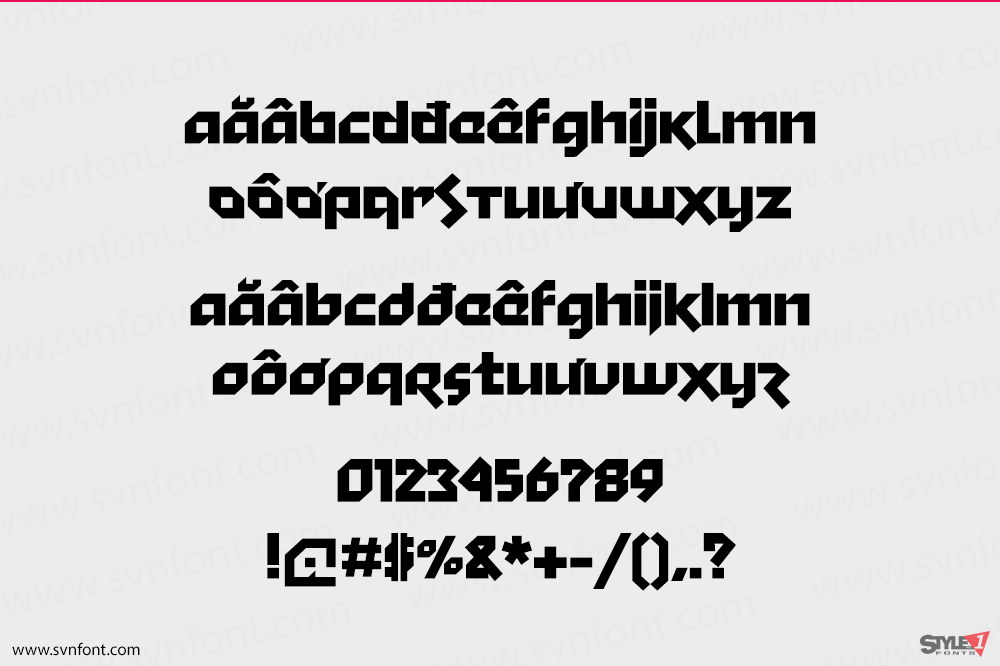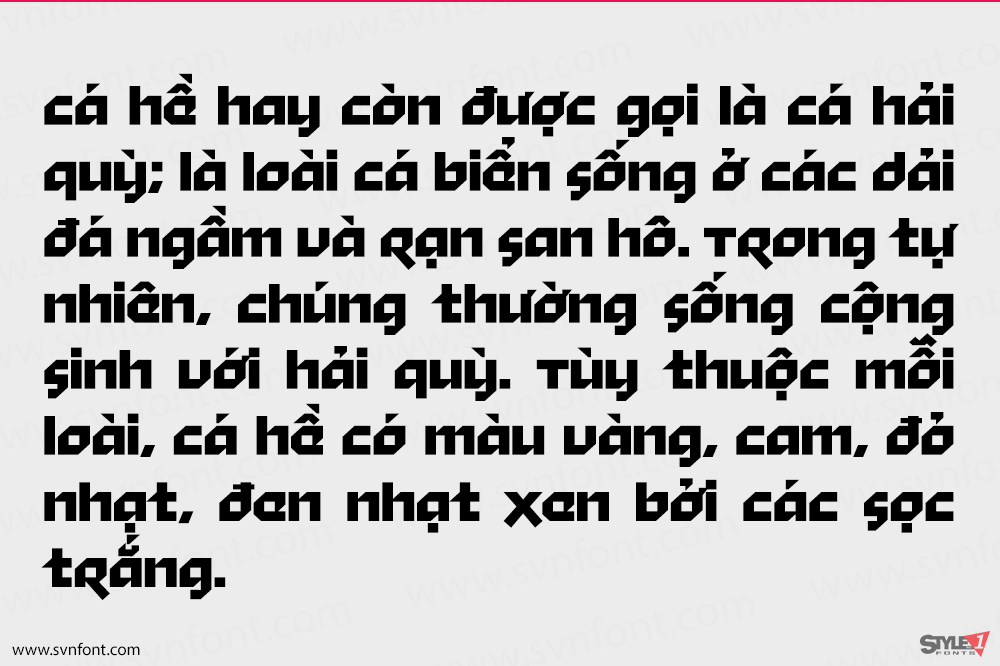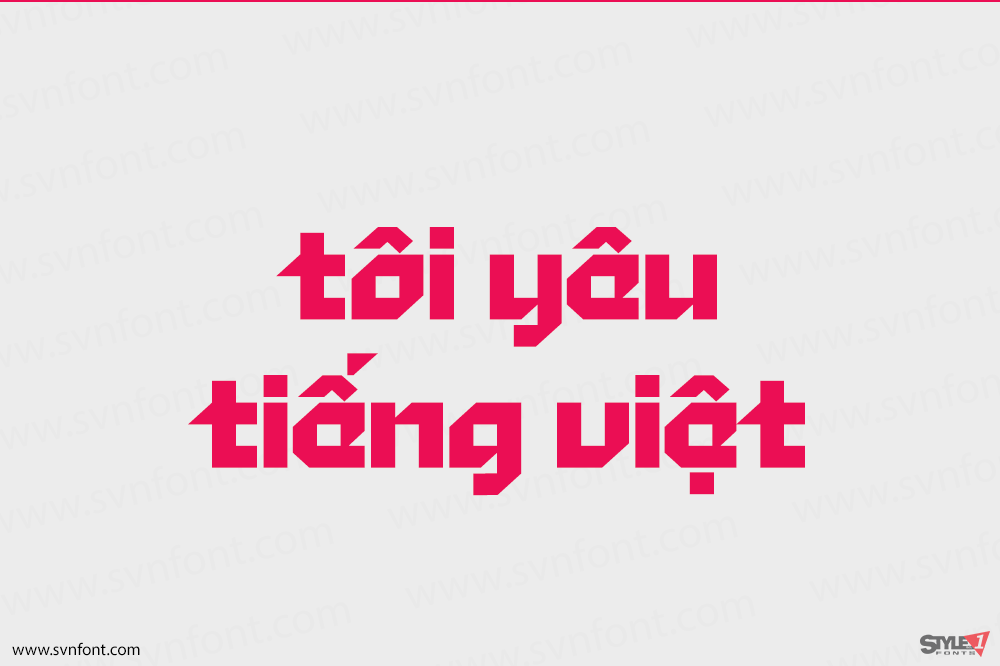
Stiff Staff là một font display khá khác biệt, font chữ chỉ gồm chữ in thường, được tạo ra từ những nét chữ vuông vức kết hợp vát nhọn một cách sắc bén. Font thích hợp cho các thiết kế về trò chơi điện tử, hoạt hình…
Nhà thiết kế: Borislav Alexandrov
Nhà phát hành: Fontfabric
Việt hóa từ bản gốc từ Fontfabric